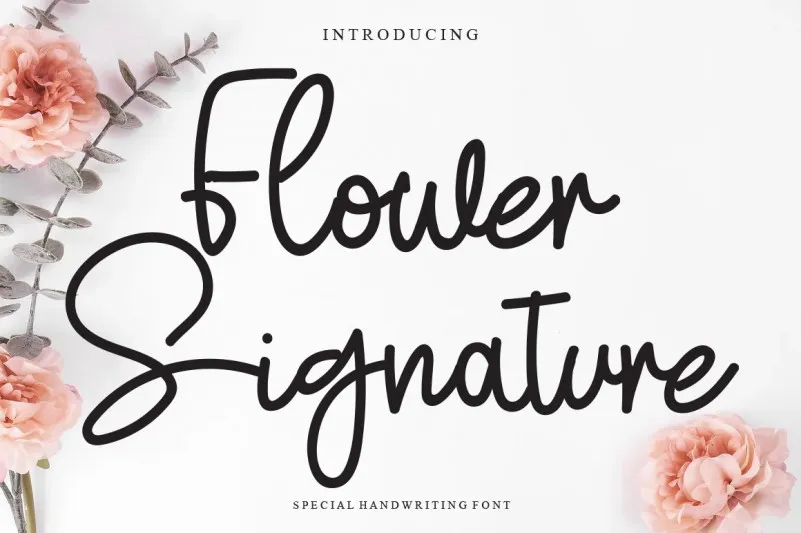
Flower Signature Font – Download Grátis
A fonte “Flower Signature Font” é uma elegante e suave tipografia cursiva criada pelo designer levincreative. Suavemente curvada, esta fonte se destaca por seu fluxo fluido e elegante, tornando-a perfeita para estilos de design como rótulos de moda ou editoriais, garantindo um resultado impecável. Se você está buscando adicionar um toque único e sofisticado aos seus projetos, essa fonte é uma escolha ótima. Sua facilidade de leitura torna-a ideal para aplicações variadas, desde rótulos em lojas até capas de livros. Adicione-a à sua próxima tarefa e aprecie o resultado impecável que ela proporcionará ao seu design.